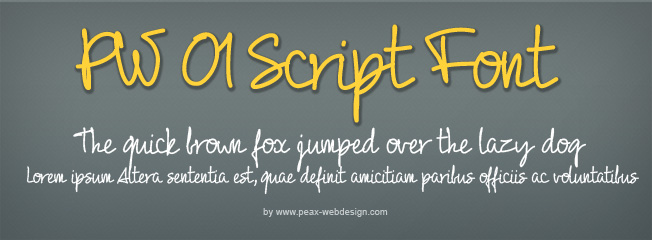
PW 01Script est une nouvelle typo manuscrite, souple et déliée, que vous pourrez utiliser gratuitement à titre personnel. Pour un usage commercial, merci de bien vouloir me contacter. N'hésitez pas à partager le lien !